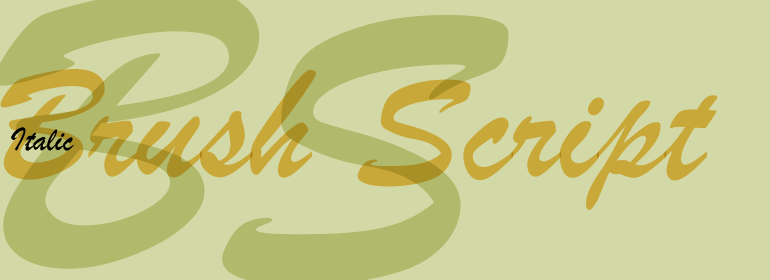
Brush Script
Brush Script,这款字体结构工整、笔画清晰,兼顾美观与易读性,适用于标题、正文、海报、包装、LOGO 等多种场景。字形优雅稳定,风格百搭耐看,适配日常排版与创意设计,让文字呈现更舒适、更具质感。Brush Script一笔一画,皆是细节,以均衡的比例、流畅的线条打造舒适视觉体验,字形端正大气,风格简约现代。无论是商业设计、品牌宣传还是日常排版,都能轻松驾驭,让文字更有格调与力量。Brush Script字体下载。
字体品牌: Bitstream(Monotype) 设计师:Smith,Robert E. 字体分类: 字体属性:外文 字符集:Unicode 发布时间: 2018